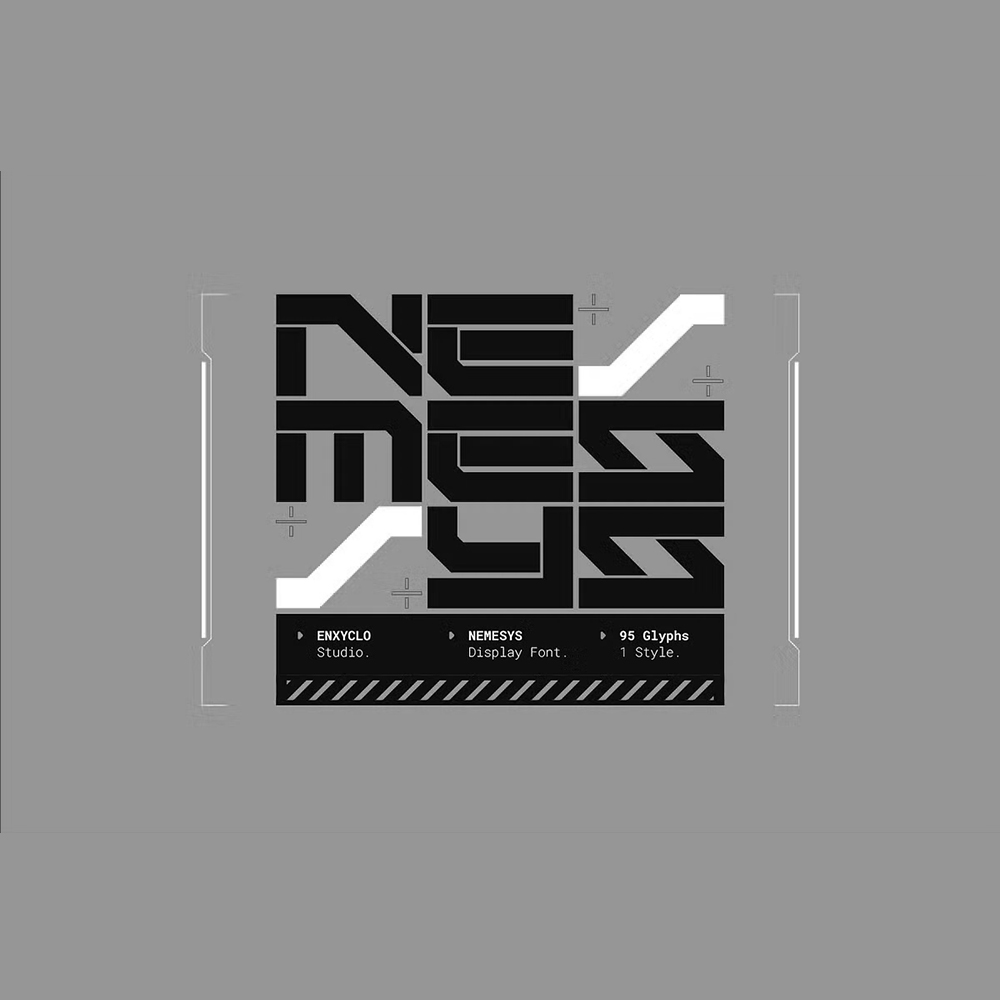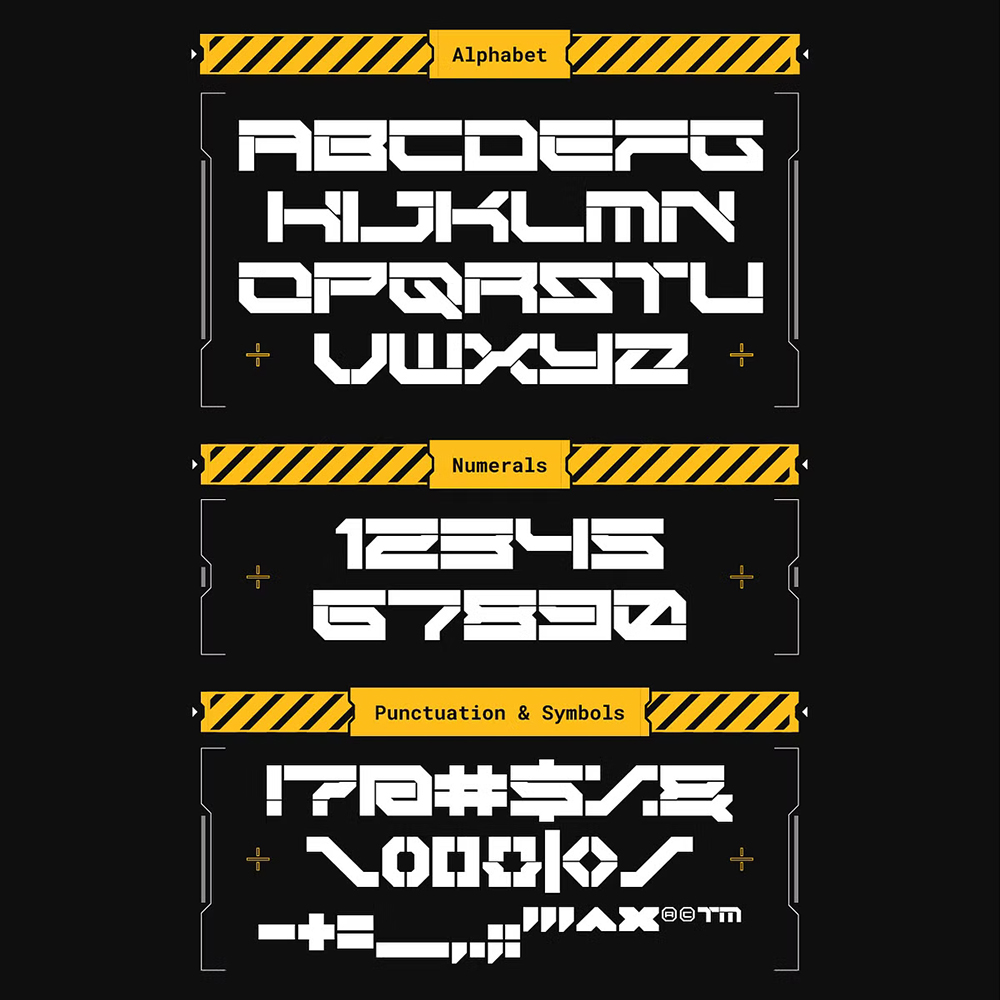
فونت پرمیوم و انگلیسی Nemesys Font یک فونت نمایشی آیندهنگر است. این فونت به شدت از حال و هوای صنعتی و رباتیک الهام گرفته شده است.…
فونت پرمیوم و انگلیسی Nemesys Font یک فونت نمایشی آیندهنگر است. این فونت به شدت از حال و هوای صنعتی و رباتیک الهام گرفته شده است. طراحی فونت، پروژه شما را قدرتمندتر و الهامبخشتر میکند. این فونت برای تیتر، بیلبورد، مجلات، وبسایت، عناوین، پوستر، برندسازی، تصویر بندانگشتی، طراحی تیشرت، طراحی لباس خیابانی و لوگوهای خلاقانه یا هر پروژهای که نیاز به لمس آیندهنگرانه دارد، عالی است. با این فونت نمایشی زیبا و آیندهنگر، کاملاً میتوانید پروژه خود را از بقیه متمایز کنید.